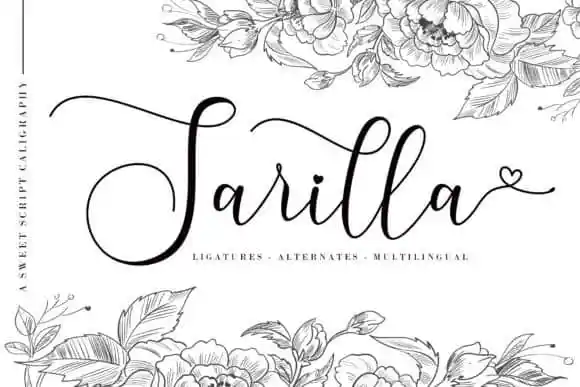
Sarilla Calligraphy Font – Fonte Grátis
Sarilla Calligraphy Font
A Sarilla Calligraphy Font é uma preciosidade para designers buscando adicionar uma nota romântica a seus trabalhos. Esta elegante tipografia de script foi cuidadosamente criada pela AEN Creative Studio, apresentando características bem balanceadas e lindas que se combinam perfeitamente em designs diversos. Sujeitosa como o nome sugere, esta fonte oferece um amplo espectro para seus usos, facilitado pelo suporte PUA, permitindo acesso a todos os caracteres e ascentes de forma fácil e intuitiva. Seria uma excelente escolha para qualquer projeto que busca trazer personalidade ao seu design, seja em cartões de aniversário, gráficos ou até mesmo em elementos de marca digital.